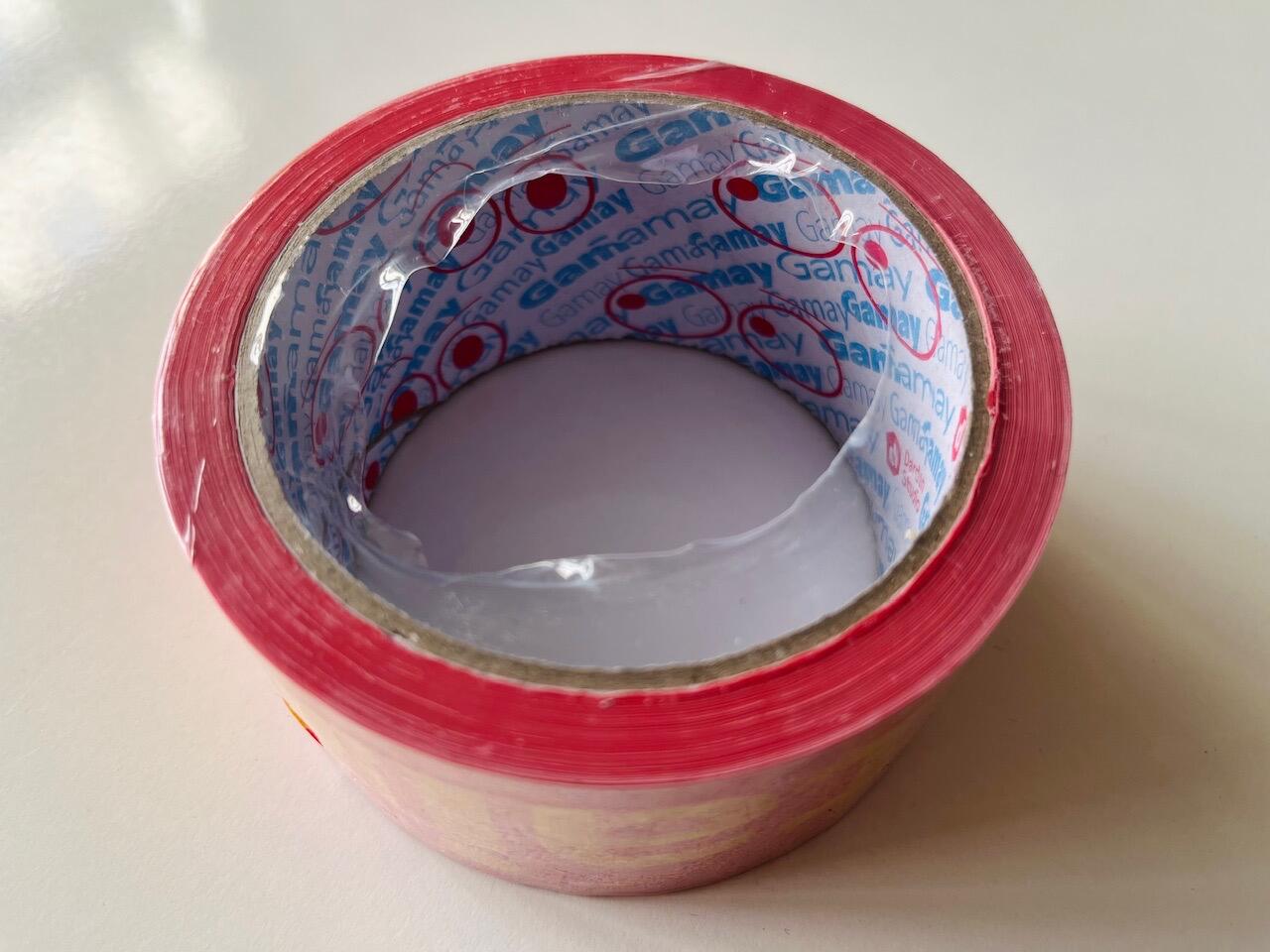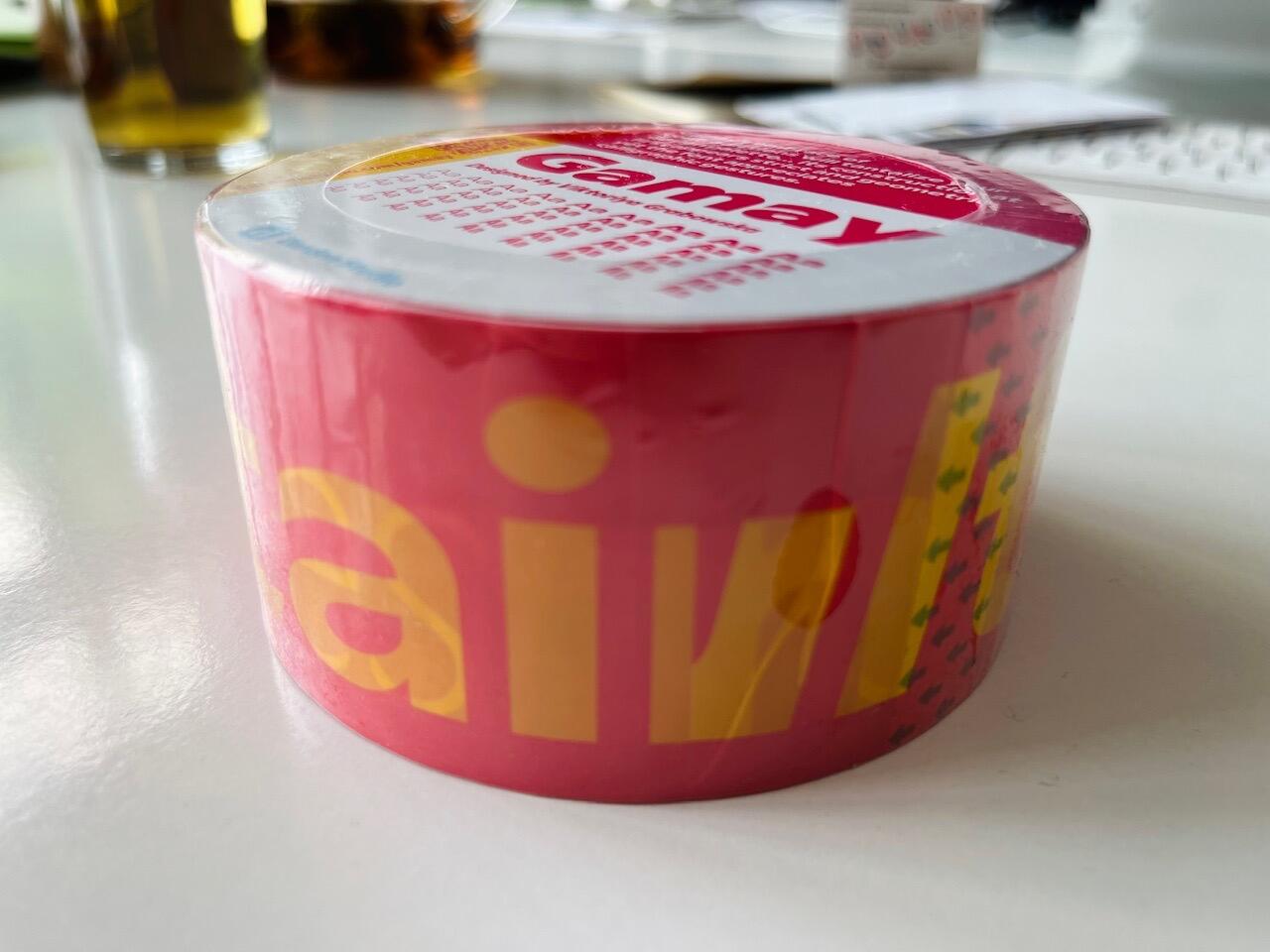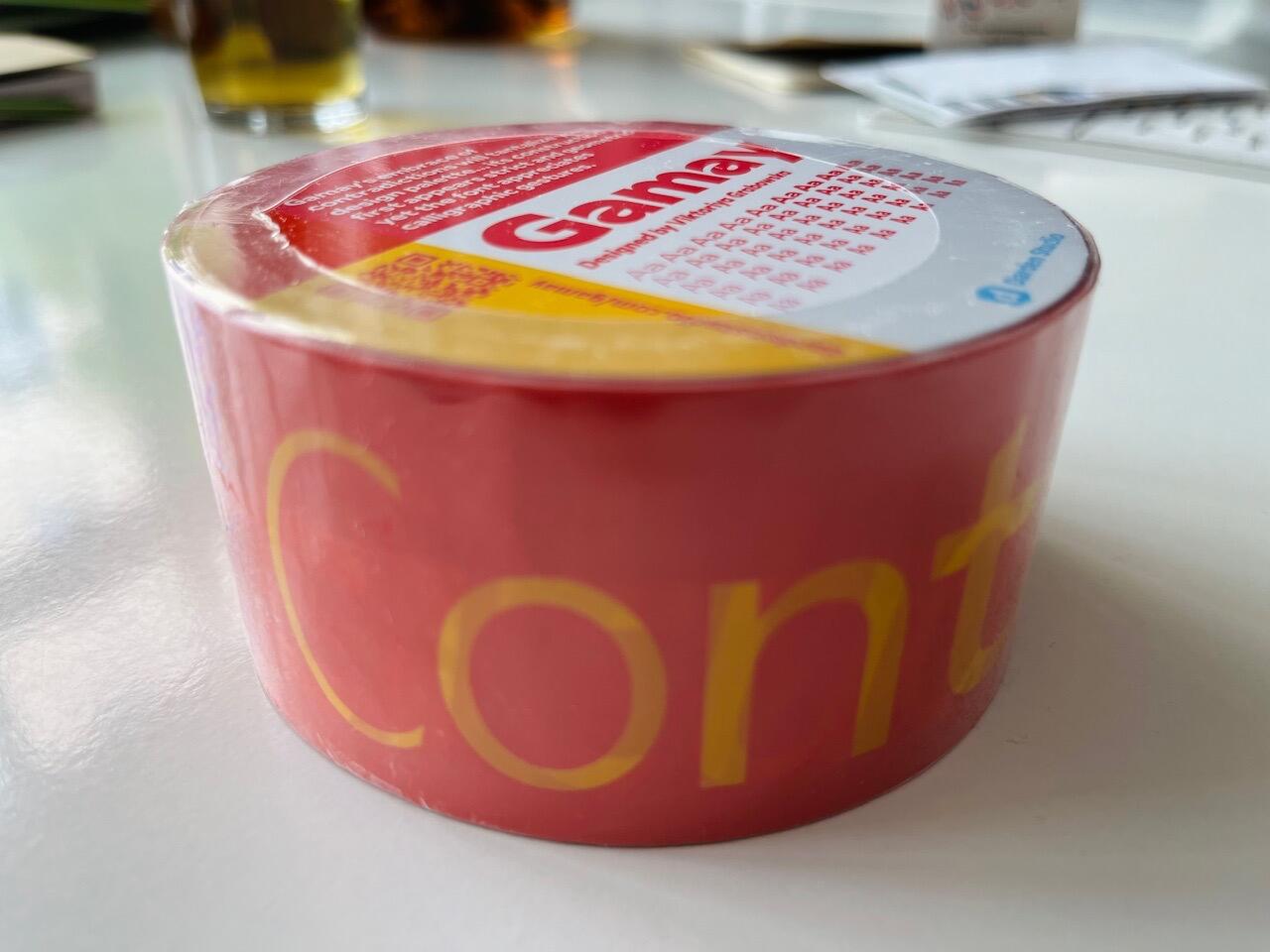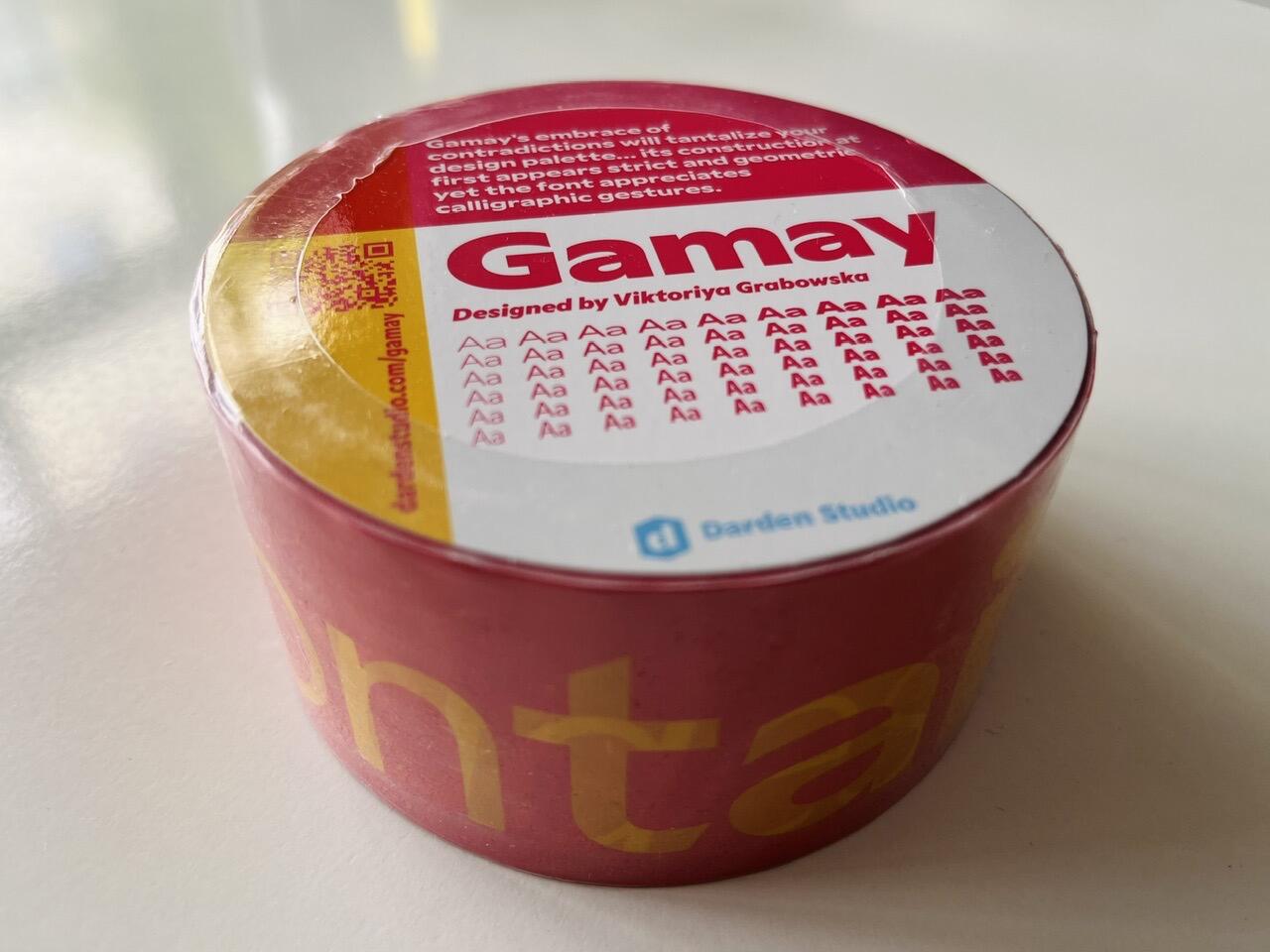
vor 4 Minuten schrieb Ralf Herrmann:
Gibt es da eine zugehörige Shop-Seite oder ähnliches?
Ich hab den Link vom QR-Code gerade ergänzt …
Ach so ... keine Ahnung ob man das Klebeband kaufen kann. Hat eine Freundin von der Typographics 2024 aus New York mitgebracht. Wenn du ne Quelle hast besorg eins für mich mit! Das fotografierte gehört mir leider nicht.